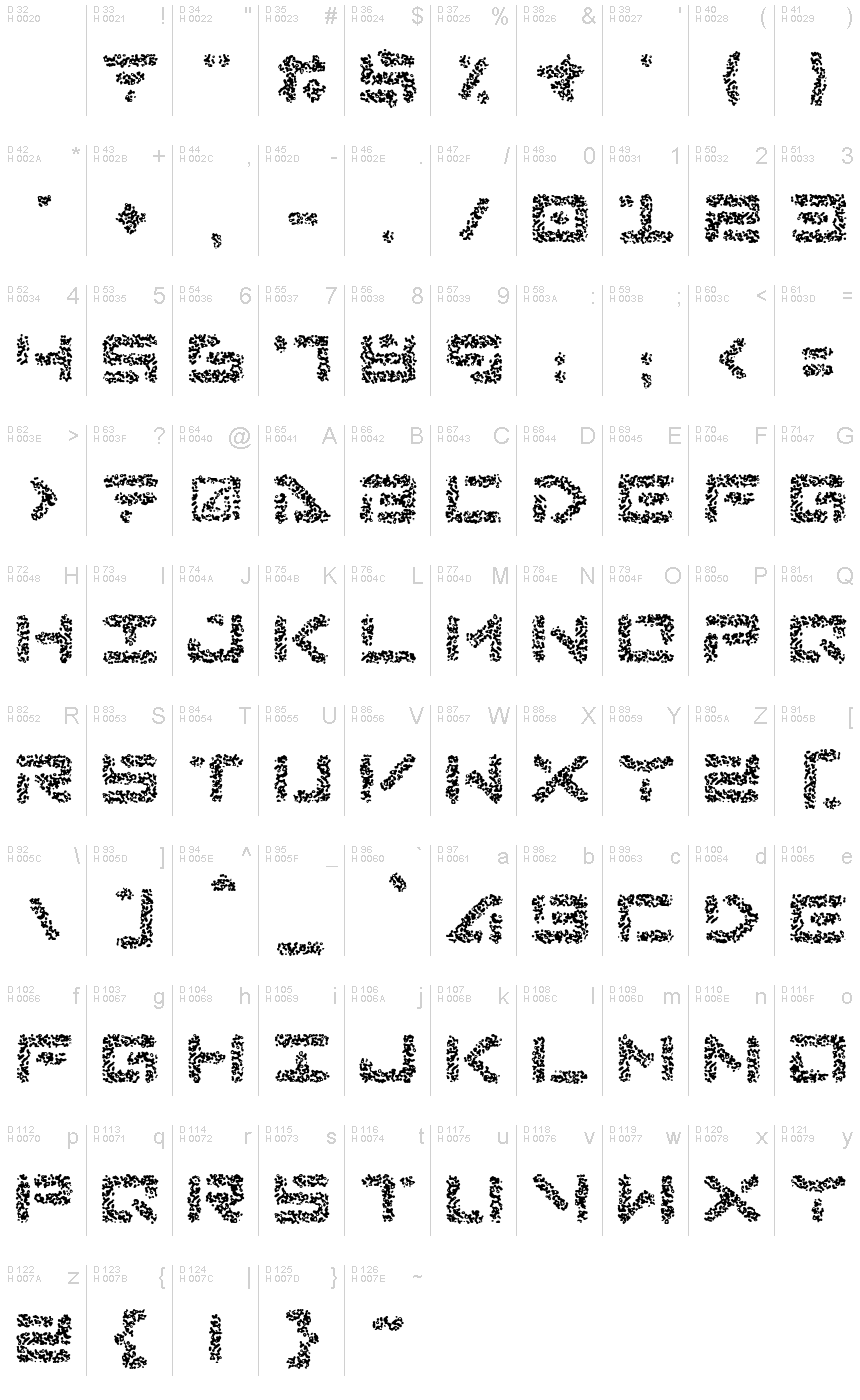
Abduction IV ist eine fesselnde Display-Schrift, die eine beeindruckende futuristische Ästhetik ausstrahlt. Die abgenutzte, körnige Textur der Buchstaben erinnert an Verfall und Verwitterung und verleiht der Schrift eine geheimnisvolle, mysteriöse Note. Mit ihren kantigen Formen und einzigartigen Details ist diese Schrift die ideale Wahl für Projekte, die eine unverwechselbare und auffällige visuelle Identität suchen.
Die Vielseitigkeit von Abduction IV zeigt sich in einer Vielzahl von Anwendungen, von Sci-Fi-Branding und Verpackungsdesign bis hin zu markanten Überschriften und Postern. Ihre Fähigkeit, eine avantgardistische und unheimliche Atmosphäre zu erzeugen, macht sie zur perfekten Wahl für Projekte, die Themen wie das Unbekannte, technologische Fortschritte oder postapokalyptische Szenarien erkunden.
This font is dedicated to the truth about abductions and the existence of extraterrestrial alien life. To see the truth, one must look at the large picture in great detail.